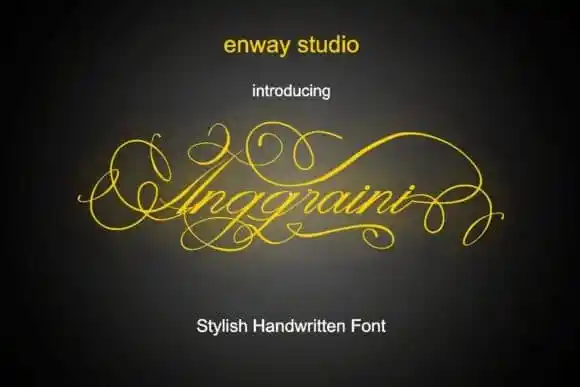
Anggraini Calligraphy Font – Download Grátis
Anggraini Calligraphy Font é uma elegante fonte feita à mão com linhas fluidas e um traçado variável no nível básico. Ela oferece linhas suaves, belos caracteres e alternativas estonteantes. Esta fonte mantém os influences do calligráfico ao mesmo tempo que adquirem um toque contemporâneo e fresco. Quer seja para gráficos de site, logotipos ou qualquer projeto de design — ela irá tornar seu trabalho destoante. Ideal tanto para designers profissionais quanto iniciantes, Anggraini Calligraphy é uma escolha perfeita para quem busca um touch elegante e moderno em suas criações.